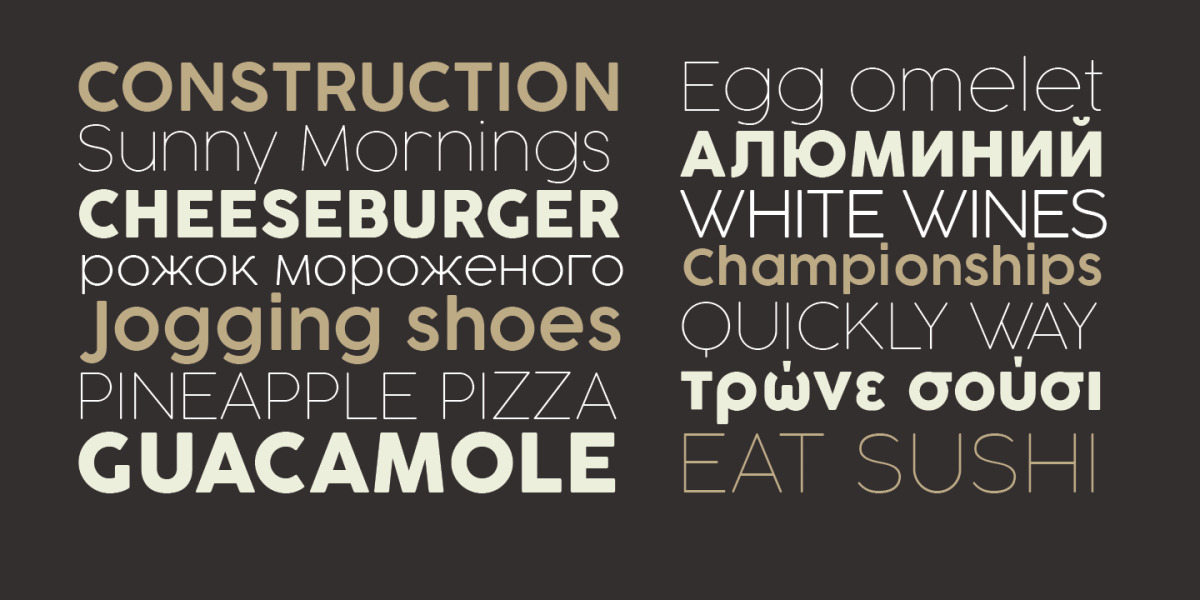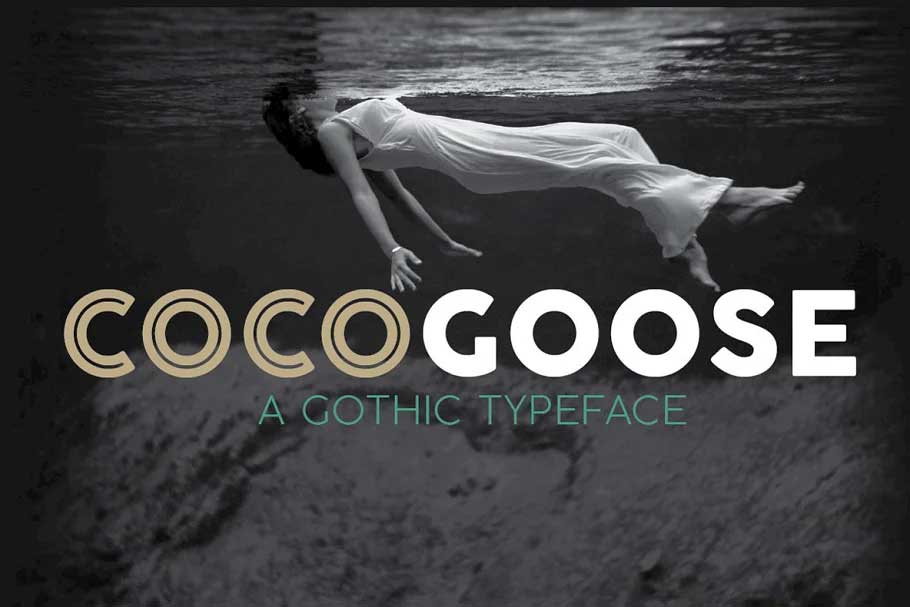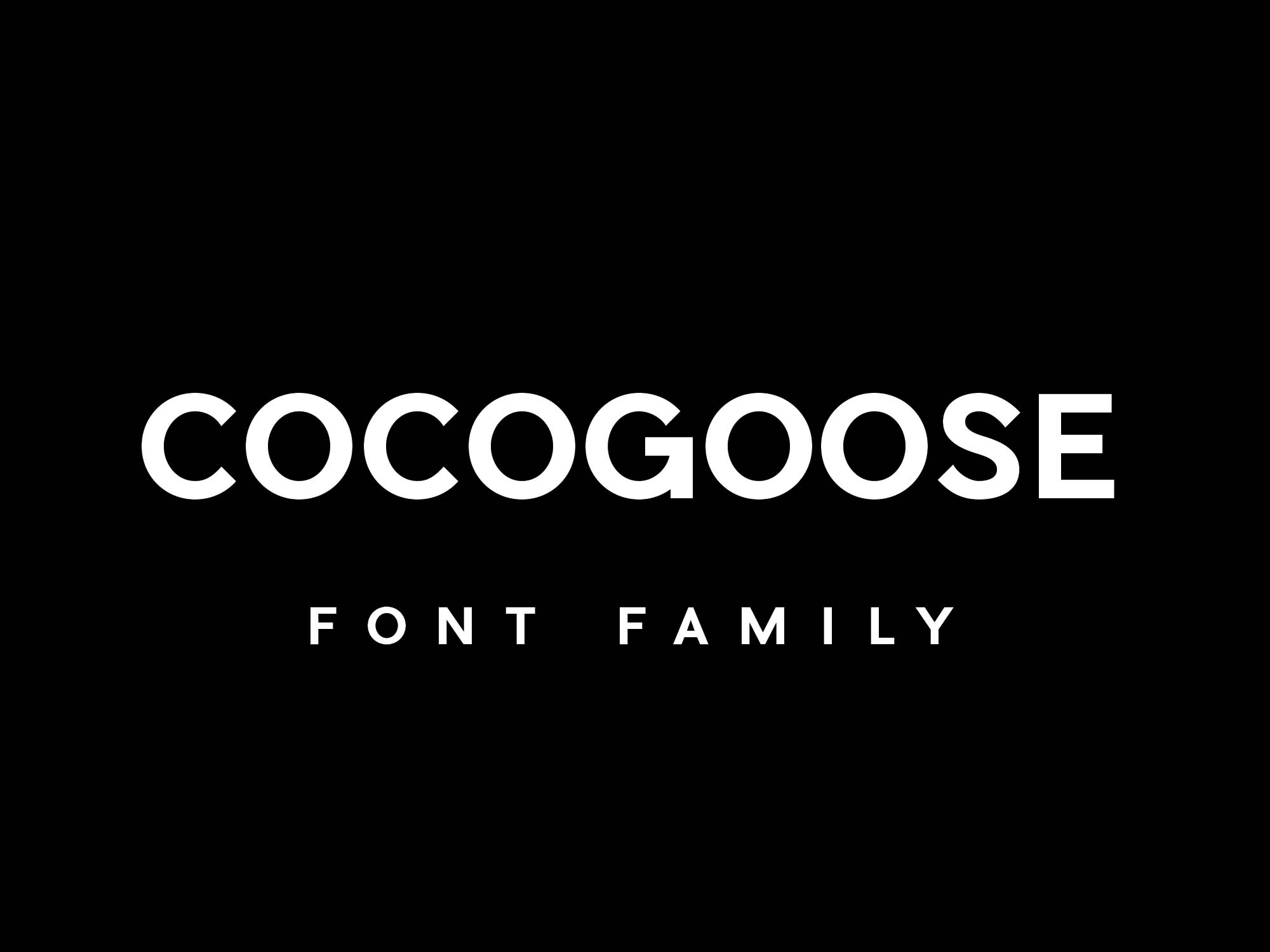
Font Cocogoose là gì?
Cocogoose là bộ phông chữ thuộc dòng Geometric Sans-serif (chữ không chân hình học) vô cùng nổi tiếng, được thiết kế bởi Cosimo Lorenzo Pancini. Đặc trưng của Cocogoose là cấu trúc chữ tròn trịa, vững chãi nhưng vẫn mang lại cảm giác hiện đại và rất “sạch”.
Với hệ thống biến thể đa dạng từ nét mảnh đến nét cực đậm, Cocogoose cho phép nhà thiết kế linh hoạt trong việc phân cấp thông tin. Bản tải font Cocogooose Việt hóa tại In Viva đã được xử lý kỹ lưỡng từng ký tự đặc thù như “đ, ư, ơ”, đảm bảo Kerning (khoảng cách chữ) cân đối.
Sử dụng font chữ Cocogoose cần lưu ý gì?
- Kiểm soát độ dày nét chữ: Cocogoose có biến thể “Block” với độ đậm cao. Khi in trên hộp đựng màu tối, bạn nên chừa lề an toàn rộng hơn để tránh hiện tượng bít mực và mất chi tiết chữ.
- Điều chỉnh khoảng cách ký tự: Với các dòng tiêu đề lớn, việc tăng nhẹ khoảng cách giữa các ký tự sẽ giúp font Cocogoose trông thoáng hơn, đồng thời tăng cảm giác hiện đại và cao cấp.
- Lựa chọn hệ màu rực rỡ: Cocogoose đặc biệt phù hợp với các tông màu neon hoặc trắng – đen có độ tương phản cao, giúp tôn lên vẻ mạnh mẽ và cá tính của thiết kế bao bì.